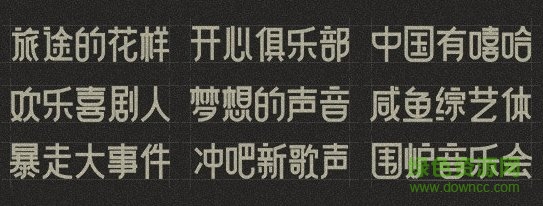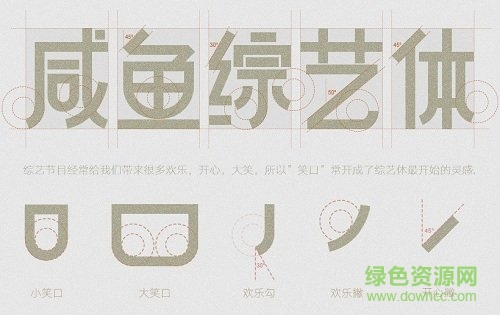
咸魚綜藝體是一款即將上線的綜藝字體,字體設(shè)計(jì)靈感來自于國內(nèi)的綜藝特色,即給人帶來了無數(shù)歡樂,整體造型端正,美術(shù)體的設(shè)計(jì)風(fēng)格讓文字更加清晰顯眼,喜歡的朋友就來綠色資源網(wǎng)試試吧!
綜藝節(jié)目經(jīng)常給我們帶來很多歡樂,開心,大笑,所以“笑口”常開成了綜藝體最開始的靈感。
咸魚綜藝體,筆畫圓潤與筆直線條結(jié)合,兼具剛硬和柔和之感,給人嚴(yán)肅而立體的生角呈現(xiàn),可以廣泛使用在平面設(shè)計(jì)、藝術(shù)設(shè)計(jì)、海報(bào)設(shè)計(jì)等場合。